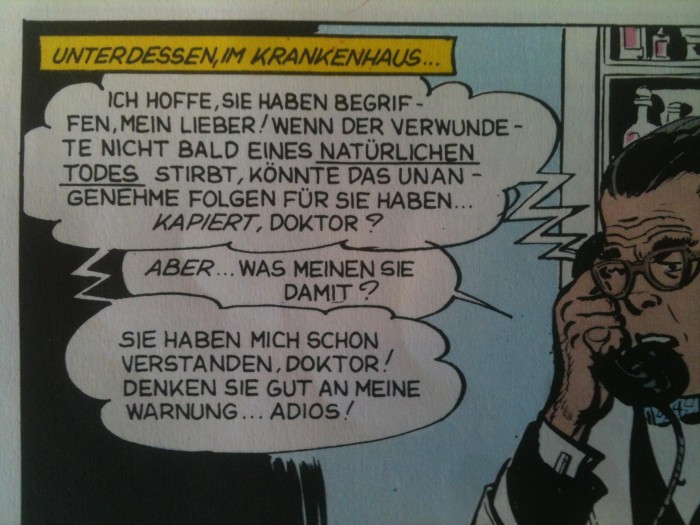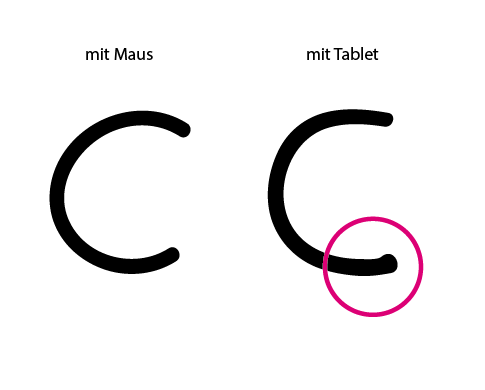
Comic Font | Brush bzw. Schreibwerkzeug
bin auf der Suche nach einem authentischen Photoshop Brush für ein Comic Font. Würde mit einem Badoo Tablet arbeiten und hätte gerne die kleinen Tropfen am Buchstavenabschluss. Vllt. ein Brush-Tipp bzw. was für Schreibwerkzeuge werden für das Lettering in Comic verwendet, wenn es kein Font ist? Alternativ würde ich analog schreiben und später digitalisieren.
Würde gern selbst eine Comic Schrift gestalten.
Die Tropfen/Strichstärkenunterschiede bekomme ich leider nicht mit einem runden Pinsel.
Vllt. mit einer Schnurzugfeder (Redisfeder)?
Wenn Du den Weg über Illustrator gehst – also erstmal eine Kontur zeichnest und in einen Konterpfad wandelst – kannst Du Dir durch das »Aufblasen-Werkzeug« viel Gefummel ersparen:
Über Doppelklick auf das Werkzeug-Symbol kommst Du zum Einstellungs-Dialog:
Links reiner monolinearer Konturpfad, rechts Tropfenform durch »Aufblasen-Werkzeug«:
Ich hab jetzt eine gute Methode mit Illustrator + Grafiktablett gefunden.
Evtl. die Variation noch erhöhen für dickere Tropfen.
Was meint ihr dazu?